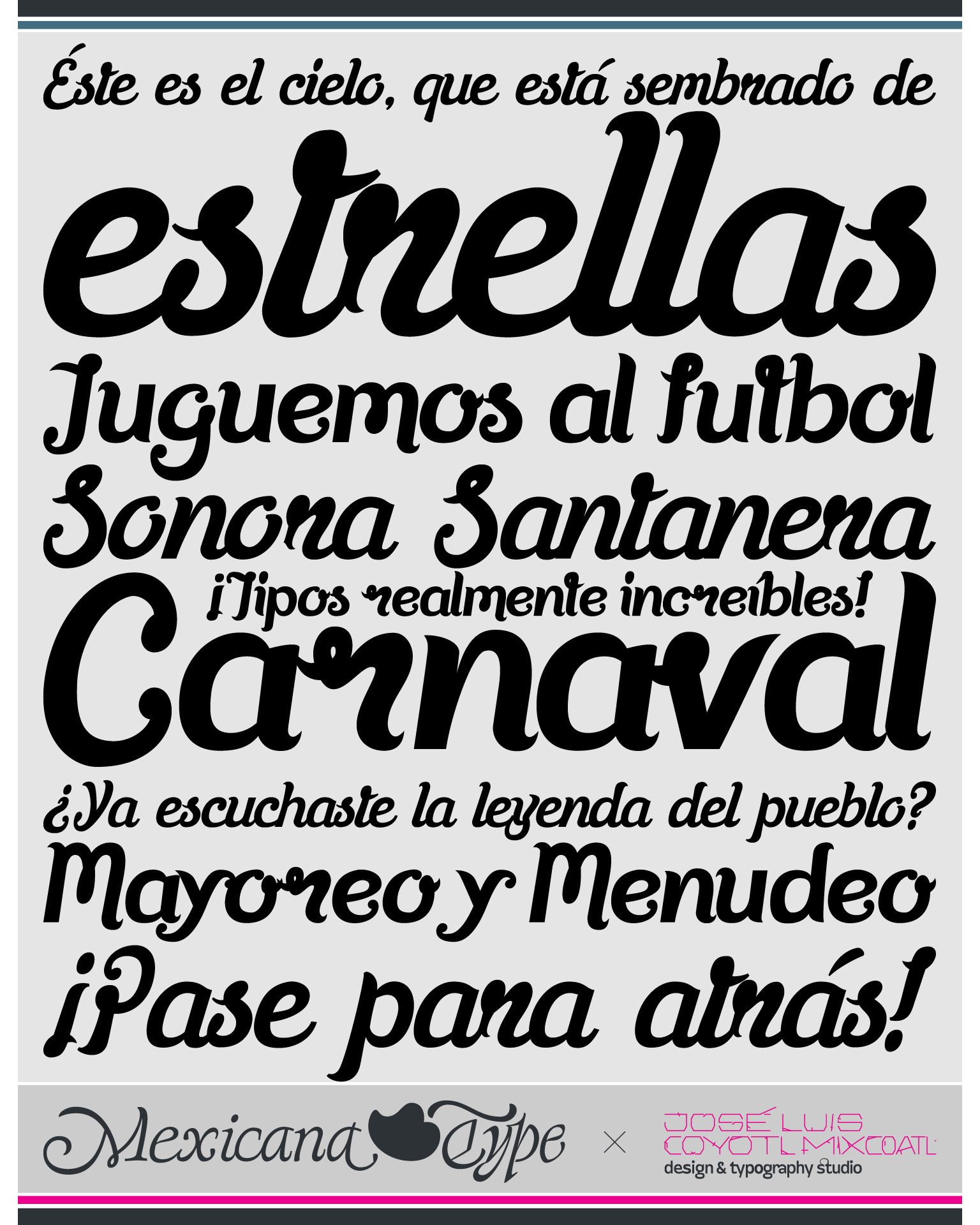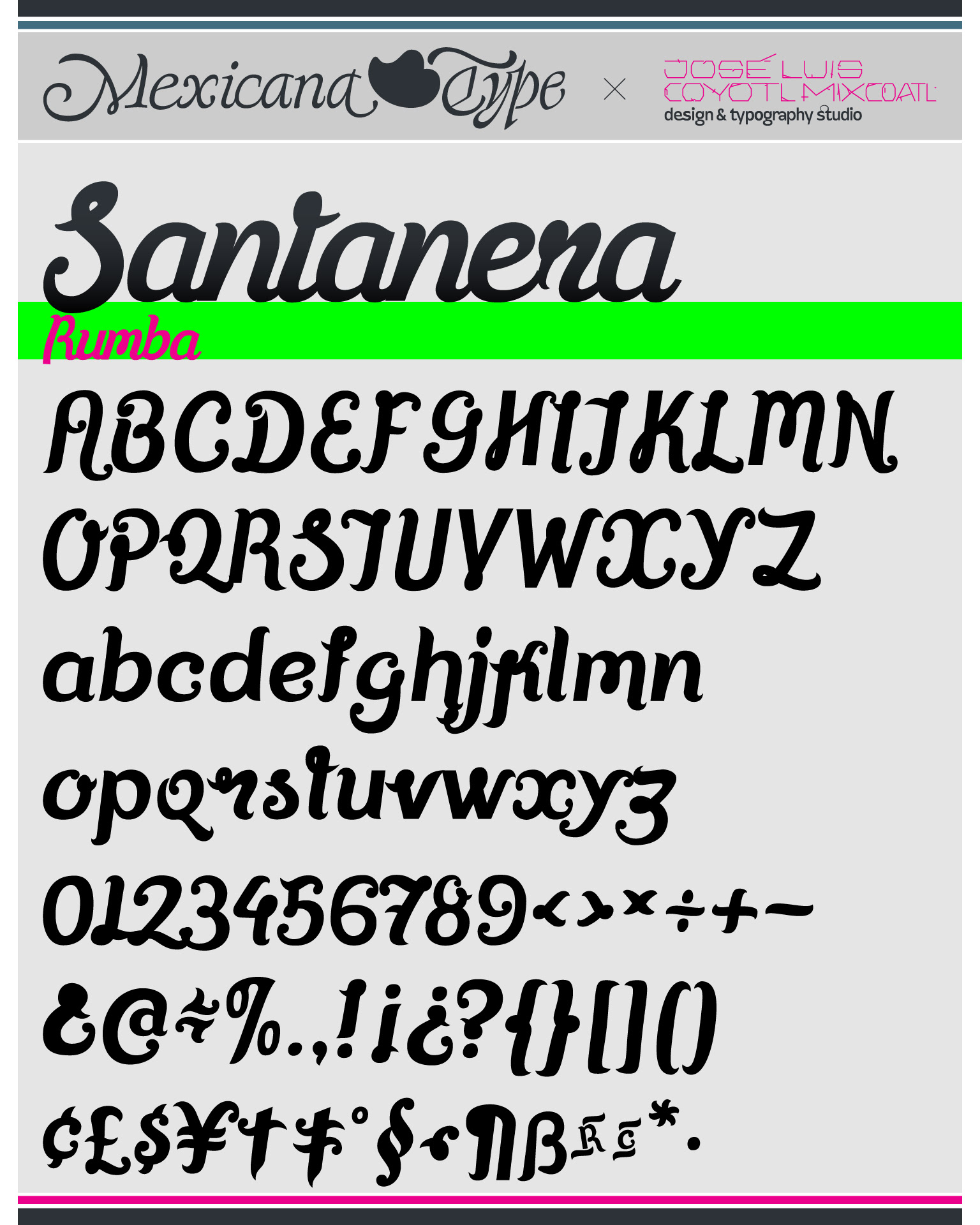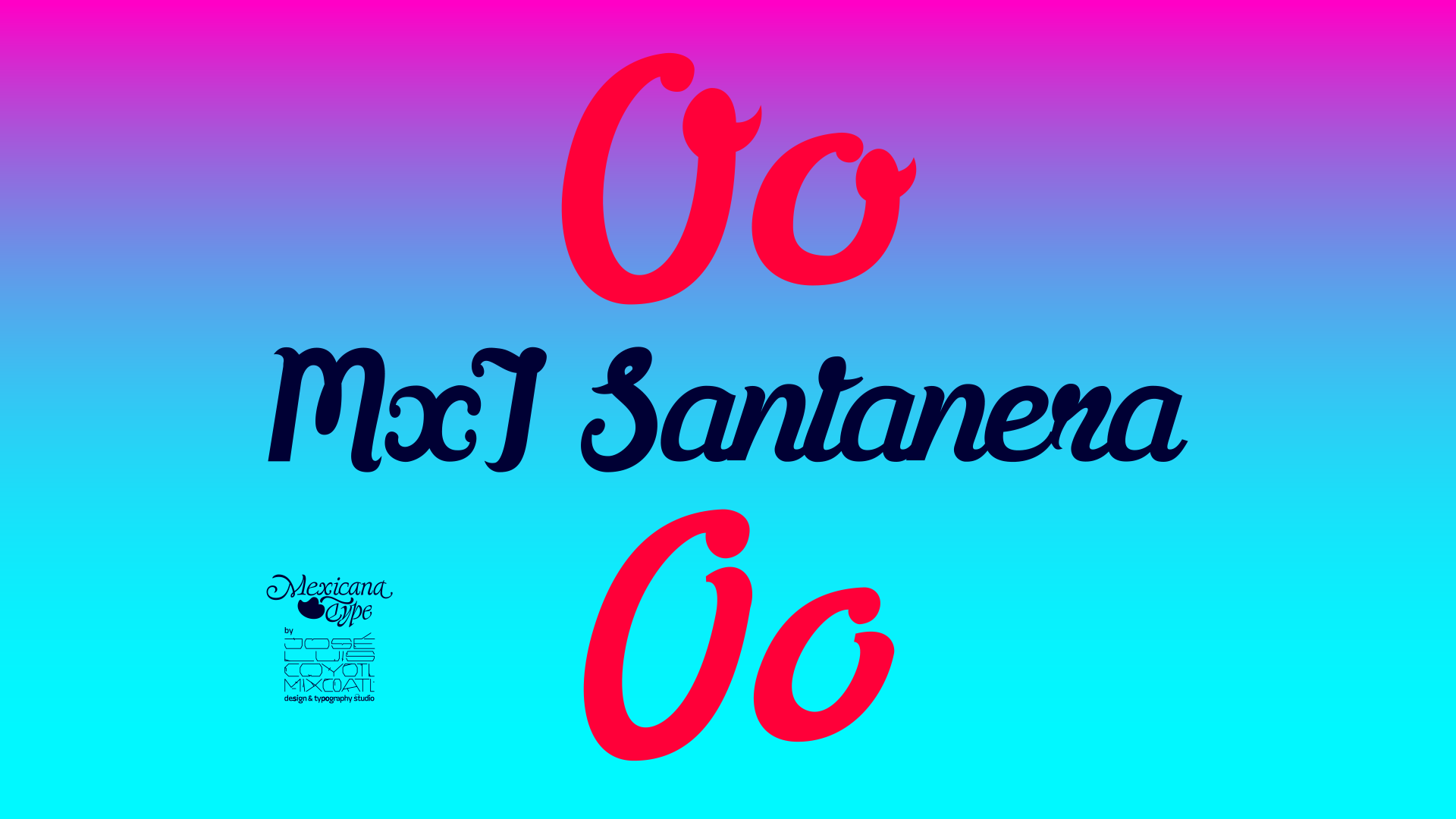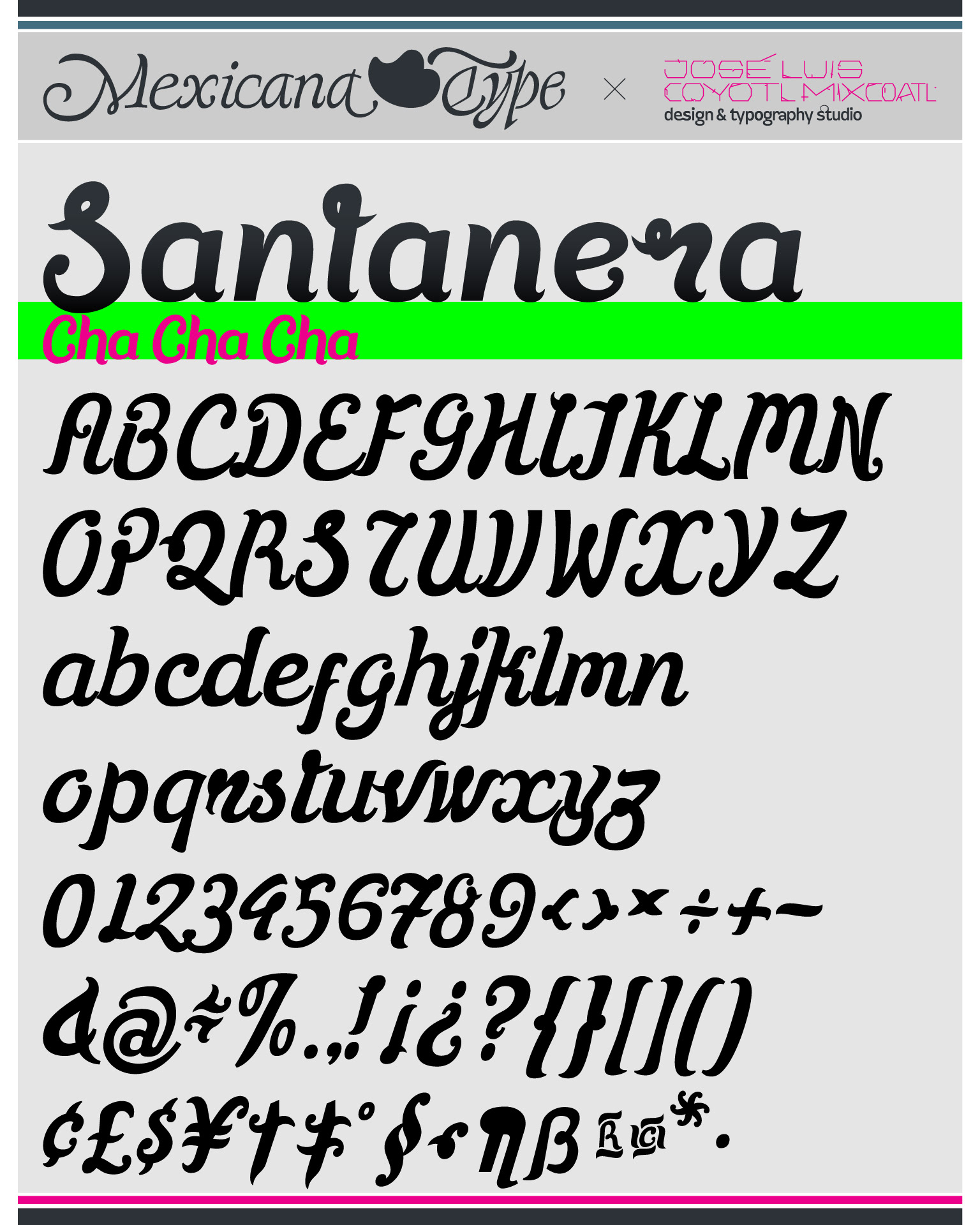
MxT Santanera fue se diseñó influenciada por las pintas en bardas para eventos populares en México, especialmente de anuncios de bailes pintados a mano fondeadas en blanco con cal y pintura vinílica y letras dibujadas con brocha, con un estilo e interpretación personal, que tuviera un sabor y trazos asimétricos, con elementos y remates rebuscados, tomando conceptos propios del baile como movimiento y ritmo, en la forma de una tipografía con reminiscencias al handlettering. Con formas bien variadas se diseñaron una variante script cuya estructura y flujo contínuo, asi como todas sus variables de formas la hacen muy dinámica, y por otro lado se creó otra con un aire mas rústico. La idea es que se vieran trazos con cierto nivel de trazados sueltos, y que resultaran en una script con una mancha tipográfica irregular pero con un contraste bien marcado para títulos.